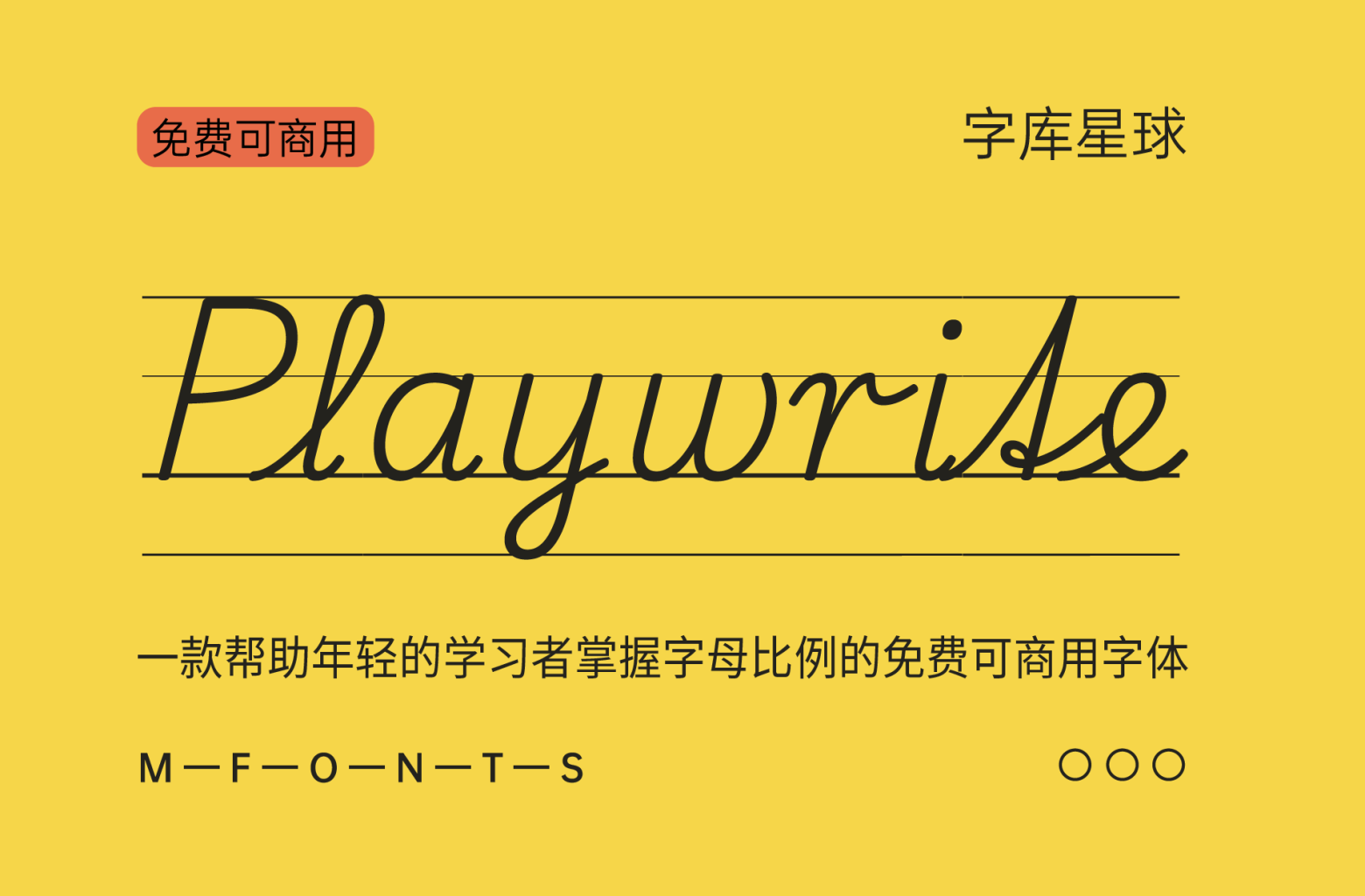
Playwrite Deutschland Schulausgangschrift Guides 是一种单重字体,旨在与其配套的Playwrite Deutschland Schulausgangschrift无缝协调。此字体在基线、x 高度、上升部和下降部上都设有指导标记,为小学生提供视觉辅助。这些指导可以帮助年轻的学习者掌握字母比例,并帮助他们自信而准确地绘制字母。
在德国,教育是由州一级而非国家一级进行监管的。每个州都定义了自己的小学书法教学模式和方法。共同的目标是在小学四年级(10-11 岁)结束时培养个人的连笔书写风格。重点是连笔书写的流畅性、字母识别和易读性,而不是对单个字母的精确模仿。
在大多数州,教师和学校可以从三种草书风格中进行选择:Ausgangsschrift (LA)、Vereinfachte Ausgangsschrift (VA)和 Schulausgangsschrift (SAS)。但在 2010 年,Grundschulverband(即小学协会)提出了一种替代的渐进式书法教学方法:Grundschrift,主要基于印刷体字体,并添加了一些草书元素,如Häckchen或出口笔画。除了占主导地位的 Ausgangschrift 系统之外,不来梅和汉堡等一些德国州还允许在学校使用这种方法。据 Das Deutsche Schulportal 称,10% 的德国学校教授 Grundschrift。
除了用于字母间距的辅助线外,所有字符都有辅助线。为了为设计带有辅助线但没有对应字母的练习纸的教师创建一种通用字体,下划线被用作关键字符。它用辅助线代替字形,并与字母间距的宽度相匹配。
Playwrite Deutschland Schulausgangschrift Guides 出现在字体菜单中,带有两个字母的国家代码“DE”和“SAS”缩写Playwrite DE SAS Guides,并具有单一常规粗细。
Playwrite 校园字体基于 Primarium 的研究成果,Primarium 是一项开创性的教育工作,记录了世界各地小学生学习手写模型的历史和当前实践。该排版引擎通过生成本地化的自由字体为教师、教育工作者和家长提供服务。Playpen Sans 是这些 Playwrite 字体的补充, Playpen Sans是一种非正式且有趣的字体,专为注释、说明和学生笔记而设计,其中还包括表情符号。